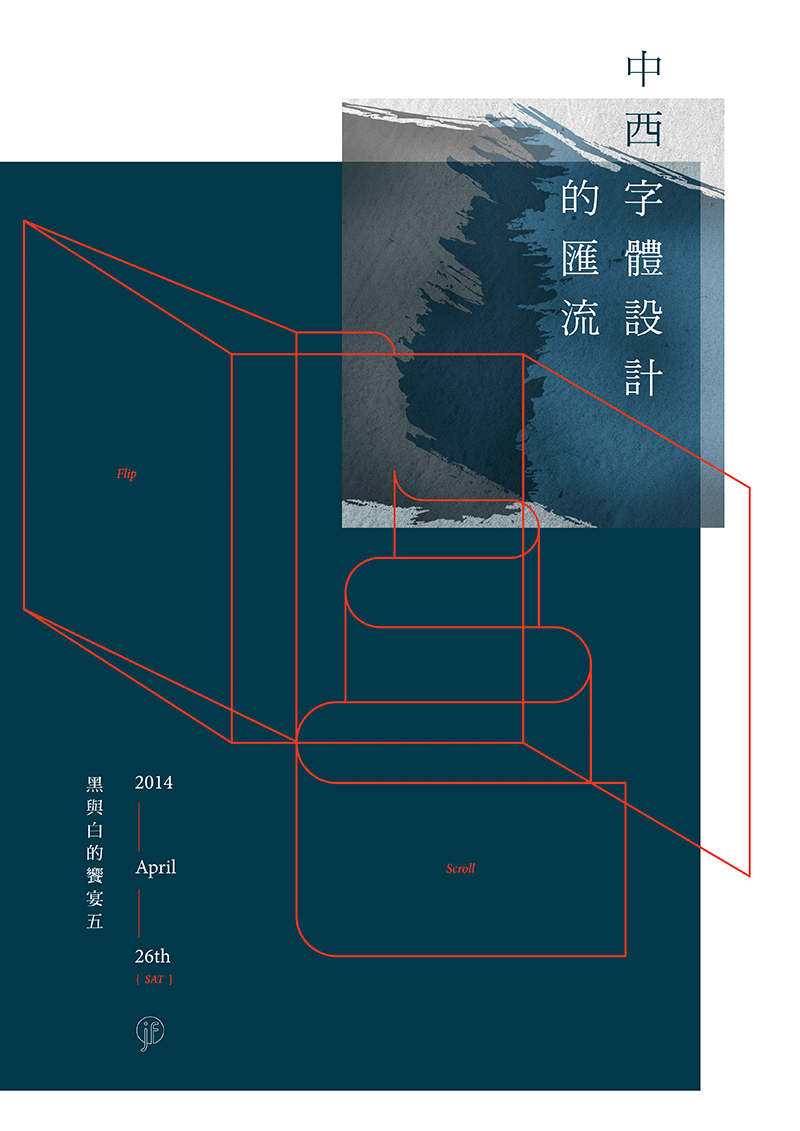
白紙蘸上墨滴的瞬間是最戲劇化的一刻,當純淨的白被打破,頓時付予另一種生命,唯有用心佈局,計白當黑,才能精彩。文字設計,一語道破,即在黑白之間力求圓滿。justfont「黑與白的饗宴」系列講座,正是專門為文字設計而生的知識饗宴。
中文、西文,各是不同文化的獨立體系,數百年的交流讓它們彼此牽動。當兩者都成為世界主要語言,與社會息息相關的設計工作,更需用心在差異中引發共鳴。但這並非容易之事,也是我們字活動舉辦開始最多人詢問的問題; 中文的字型設計者要如何掌握來自西方的 typography?又如何從文化的差異裡,重新認識我們的文字?彼此間如何借鏡,兩者間如何調和?這些都是大家常遇到的困擾問題。
第五次黑與白的饗宴,我們談西文、講漢字,也聊聊怎麼調和兩者。這次我們慎重邀請三位專精於字型的講者,與大家分享上述議題:
Joe 曾任威鋒數位 (華康字體) 字體設計師,並因熱愛字型,毅然離開工作至荷蘭留學專修 Typography(於 Royal academy of Arts ,MA Type and Media),回台灣後創立 TypeTrix (文字裏技) 。對於中英文字皆有深入瞭解的他,擅長中日文與歐語系字體設計與字體匹配規劃,目前亦為轉轉創意的資深設計兼獨立字體設計師。
Joe 非常樂於分享字體相關知識,曾在非常多字體研討聚會分享不同主題,也曾經於字戀小聚分享數次有關拉丁字體的議題,場場爆滿,座無虛席。 這一次,Joe 要從他最近熱衷並收集的黑膠唱片進行延伸,並援引在荷蘭修習的專業——拉丁字體的設計與匹配,讓大家更了解開字型學上最令人困擾的議題之一:如何進行字體匹配。
柯熾堅老師是當代中文字體設計的翹楚,知名作品包含目前仍能看到的蘋果儷黑、儷宋,在日本熱銷的華康瘦金體、超明體等,並在累積了三十年造字經驗後,花了近六年的時間製作的信黑體,推出後深獲各界好評。柯老師也是第一個設計出中文向量字體的人,在目前的中文字體設計中,處處可見到他帶來的影響,例如於擔任華康設計總監期間,決定了許多中文的排版規範,至今仍為中文設計圭臬。 這一次柯老師要帶大家深入瞭解中文字體設計的秘密。
中文字體設計的觀念是與時俱進的,在當代的字體設計觀念上已經與數年前不同,漢字設計如何讓字看起來像漢字,讓黑體字型也具備有書法的精隨?如何在字體設計的 readability 和 legibility 間取得平衡? 柯老師於字體的創造中累積一貫脈絡,這次將深入的談到字體設計的框架設計和概念差異,在圖像化、視覺化的字體充斥中,如何演變到目前信黑體的美學觀念?這次演說主題將深入的帶大家瞭解中文字體設計奧秘。